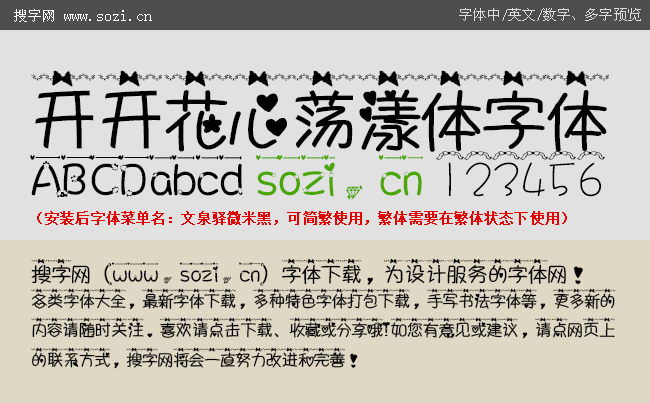
開開花心蕩漾體字體
搜字網(wǎng)給大家提供一款開開花心蕩漾體字體手機中文字體下載。這款手機字體是仿照兒童手寫風格的卡通手寫字體,字體的上下裝飾了卡通花紋。并將部分字體筆畫變成了卡通圖案,即有卡通字體的趣味性,又有手寫字體的藝術性,真是童趣十足的一款字體,特別適合喜歡手機字體個性一些的朋友在手機上安裝使用。